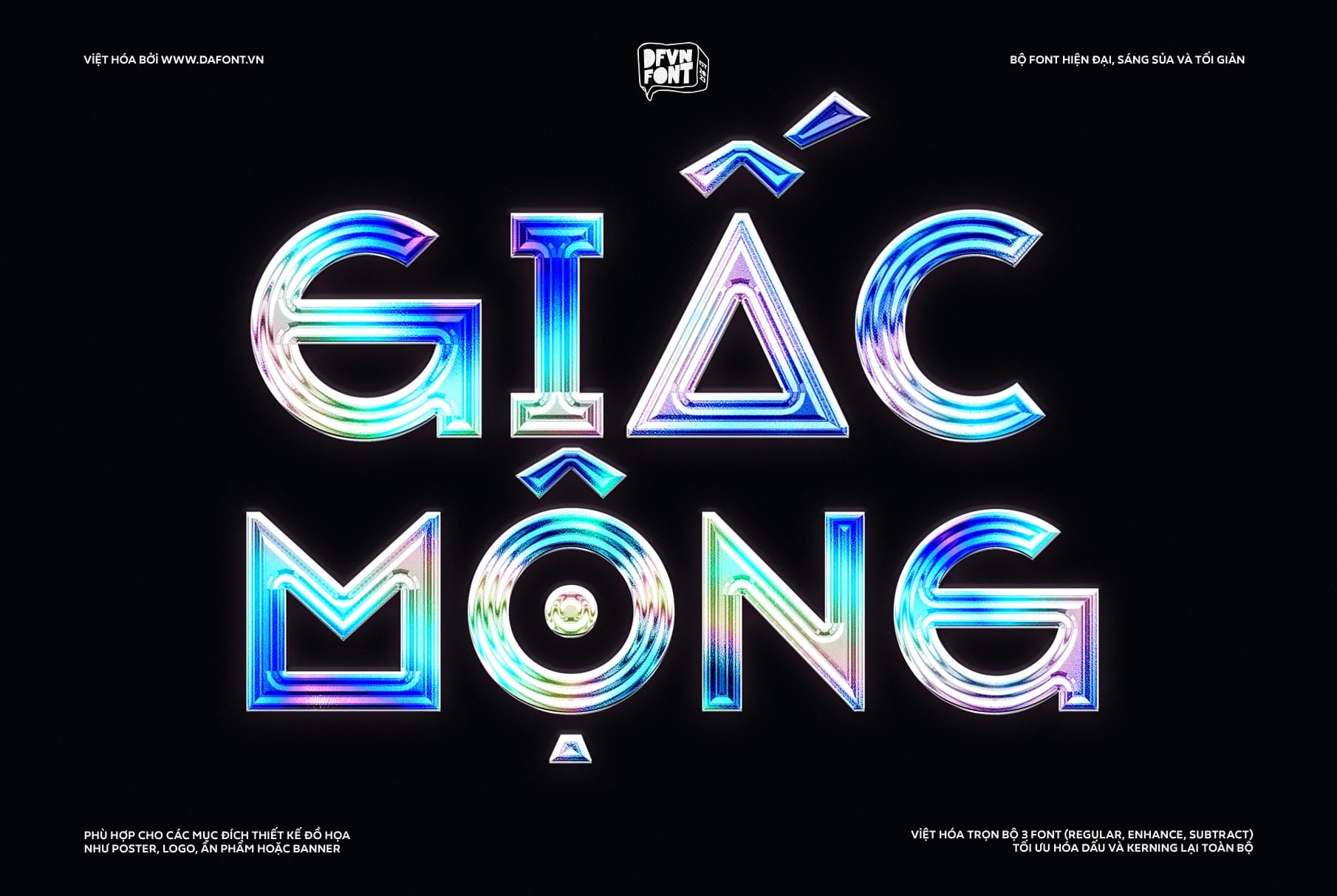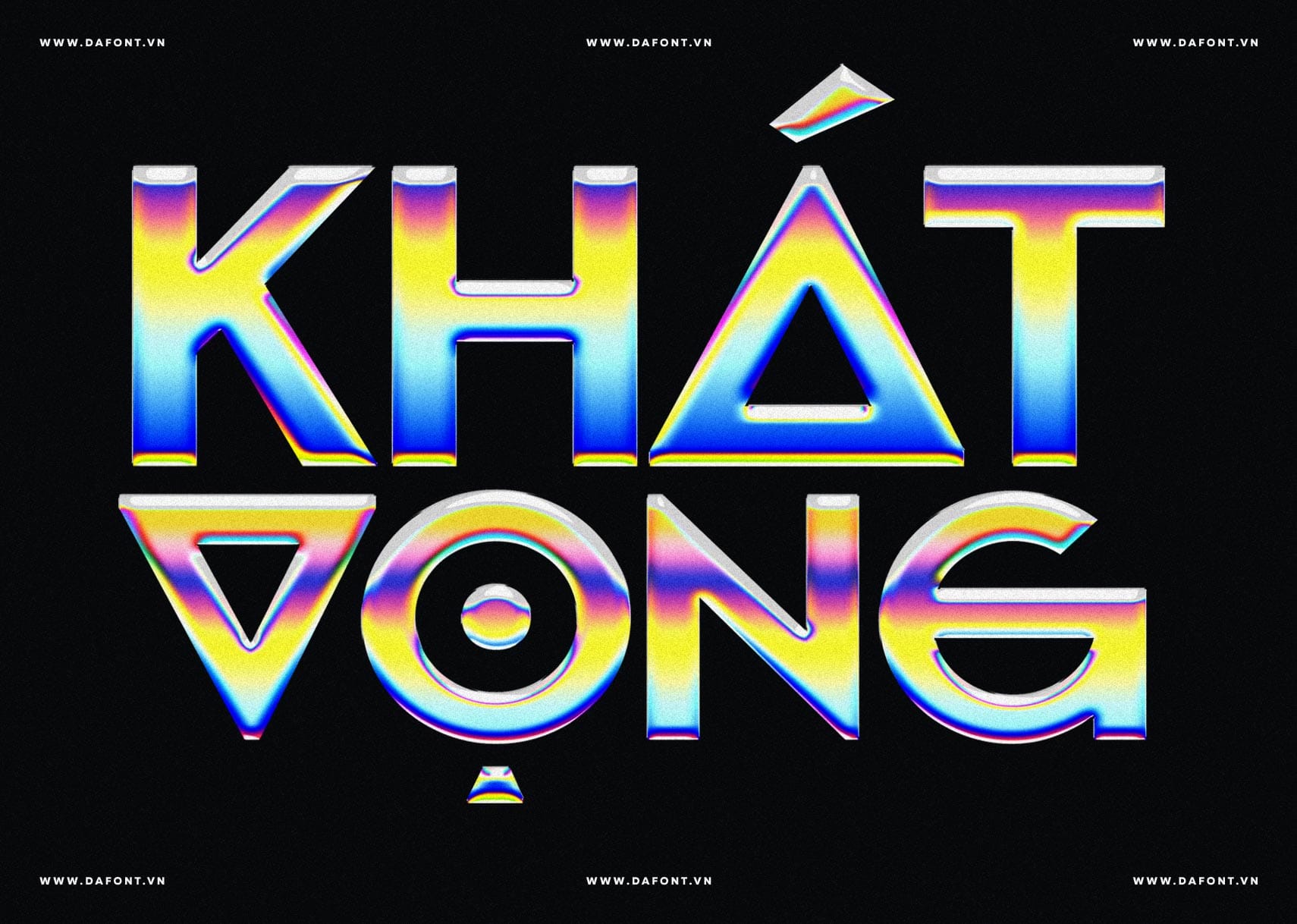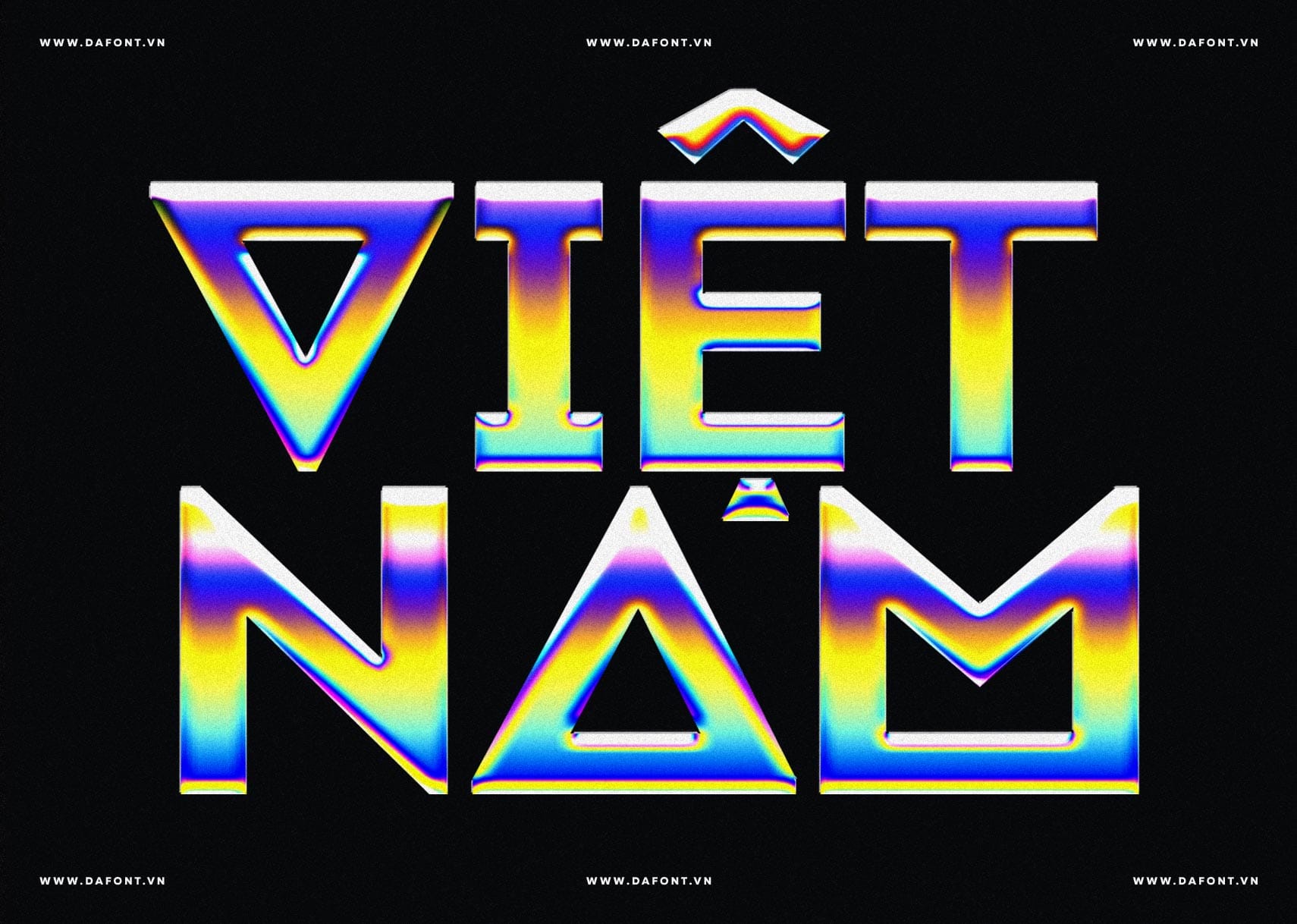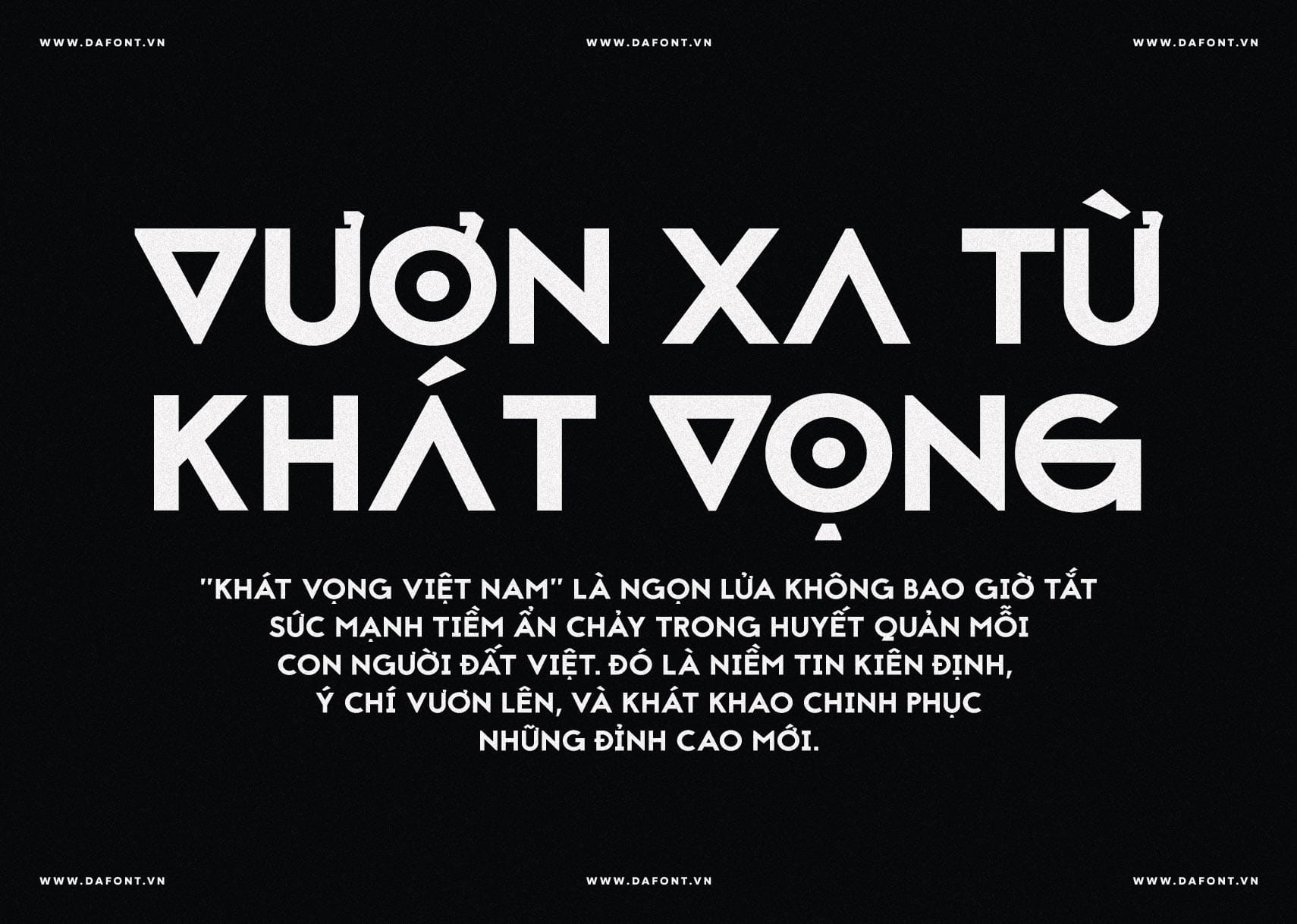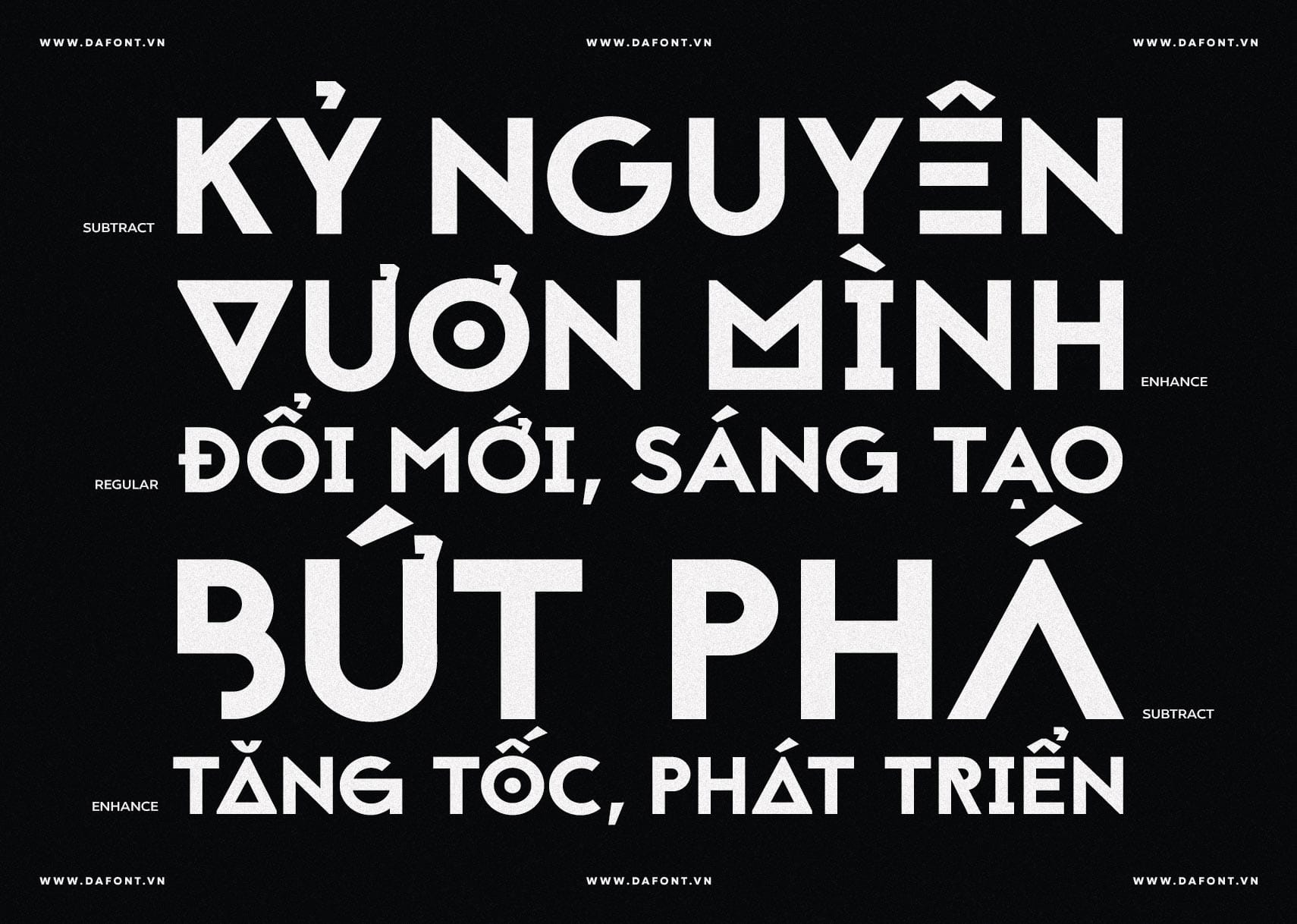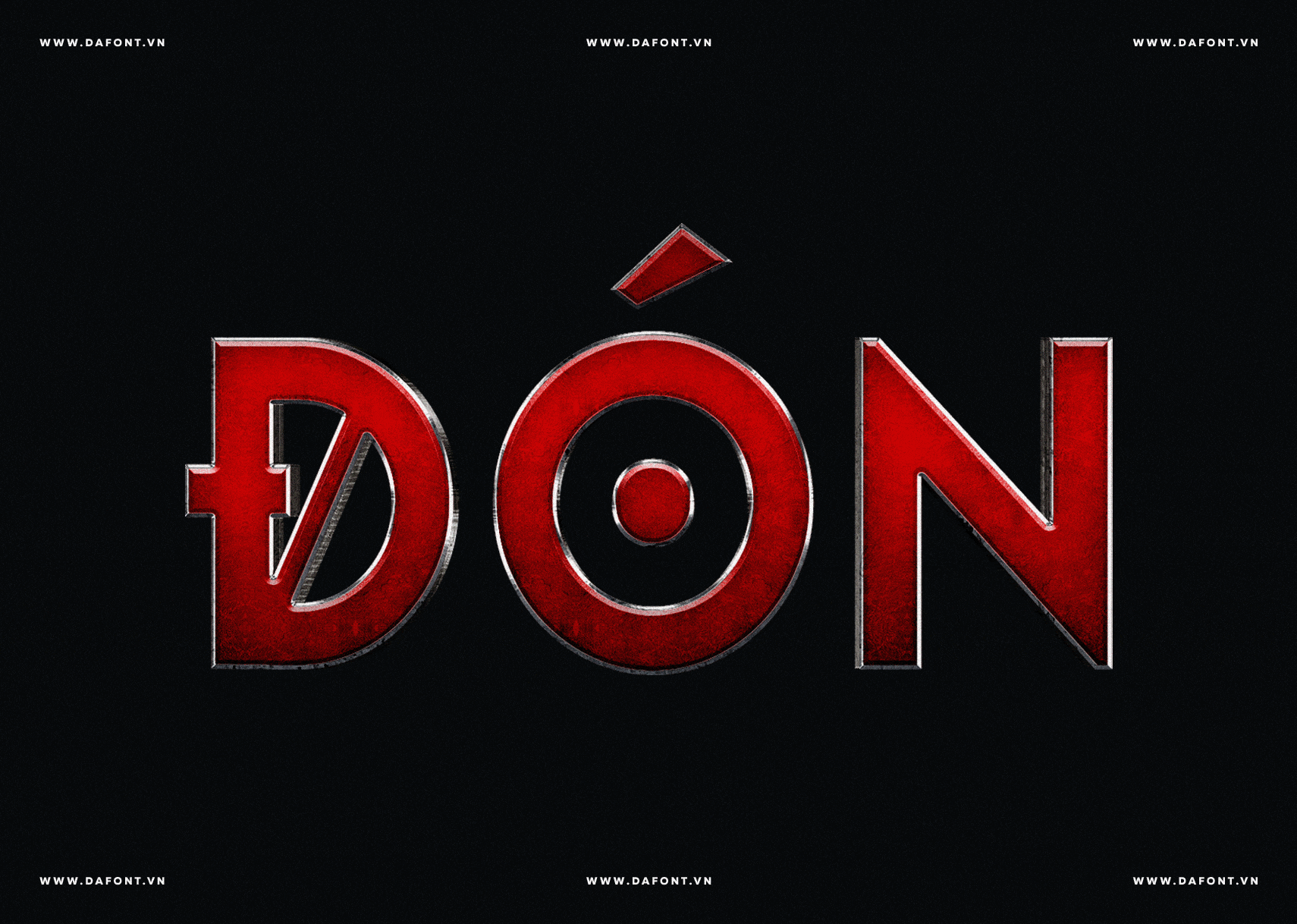
DFVN Jaapokki – bộ font sans-serif “chill” hết nấc với phong cách tối giản hiện đại, siêu hợp gu cho tiêu đề bùng nổ, poster hút mắt, logo ấn tượng. Gần đây, font này đang “hot hit” kiểu gì ấy, bản Việt hóa bị săn lùng ráo riết chỉ vì nó “say hi” cực ngầu trong game show Anh Trai “Say Hi”.
DFVN Jaapokki không chỉ có một kiểu, mà sở hữu 3 biến thể thú vị như ba “anh em” mỗi người một phong cách:
- Jaapokki Regular – “Người con cả” chững chạc, ngay ngắn, hoàn hảo cho những thiết kế cần sự chuyên nghiệp và rõ ràng.
- Jaapokki Enhance – “Anh giữa” năng động hơn, điểm xuyết vài nét sáng tạo, đủ để gây chú ý mà không mất đi sự thanh lịch.
- Jaapokki Subtract – “Cậu út” nổi loạn nhất nhà, với các đường cắt táo bạo tạo cảm giác tương lai, phá cách và đầy cá tính.
DFVN Jaapokki sở hữu tính linh hoạt cao, phù hợp cho nhiều loại dự án thiết kế từ logo thương hiệu, poster sự kiện, banner quảng cáo đến bao bì sản phẩm và giao diện website. Nhờ phong cách tối giản nhưng ấn tượng, font chữ này dễ dàng hòa hợp với nhiều phong cách thiết kế khác nhau, giúp nội dung nổi bật và tạo dấu ấn thị giác mạnh mẽ.
DFVN Jaapokki là font chữ sans-serif mang phong cách tối giản và hiện đại, nổi bật với ba biến thể cá tính: Regular tinh gọn, Enhance sáng tạo nhẹ nhàng và Subtract phá cách độc đáo. Với bộ ký tự phong phú, bản Việt hóa chuẩn chỉnh cùng kerning tối ưu, Jaapokki dễ dàng ứng dụng cho logo, poster, bao bì hay website, mang đến vẻ đẹp rõ ràng và chuyên nghiệp trong mọi thiết kế.